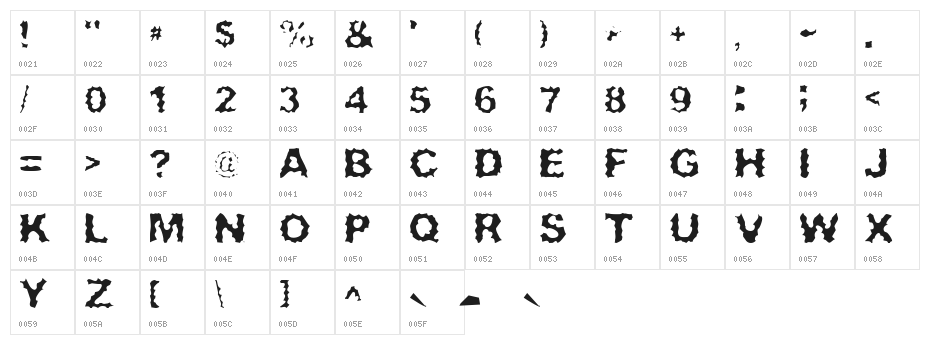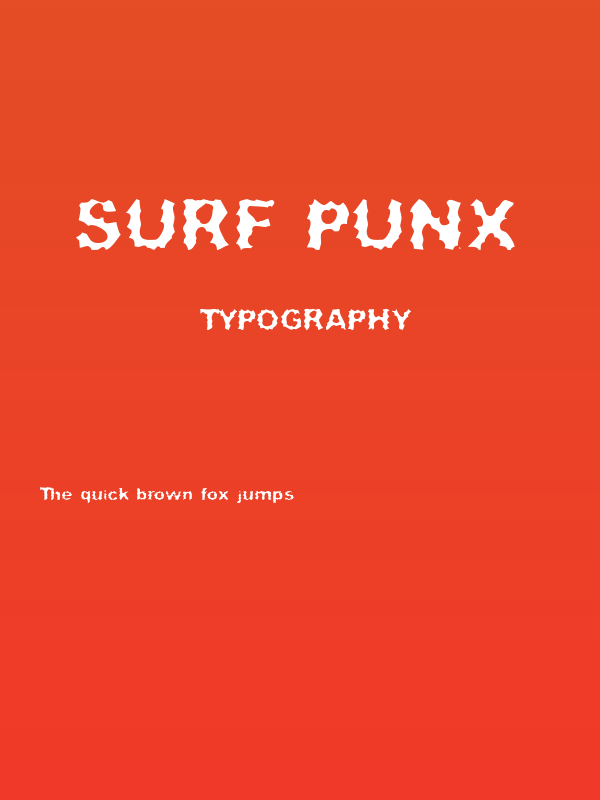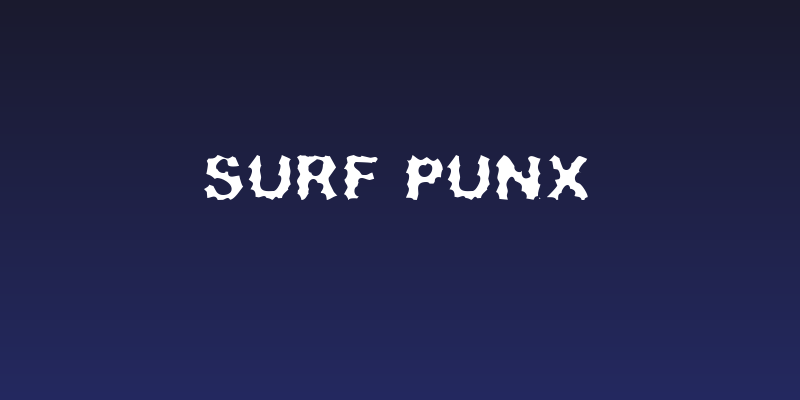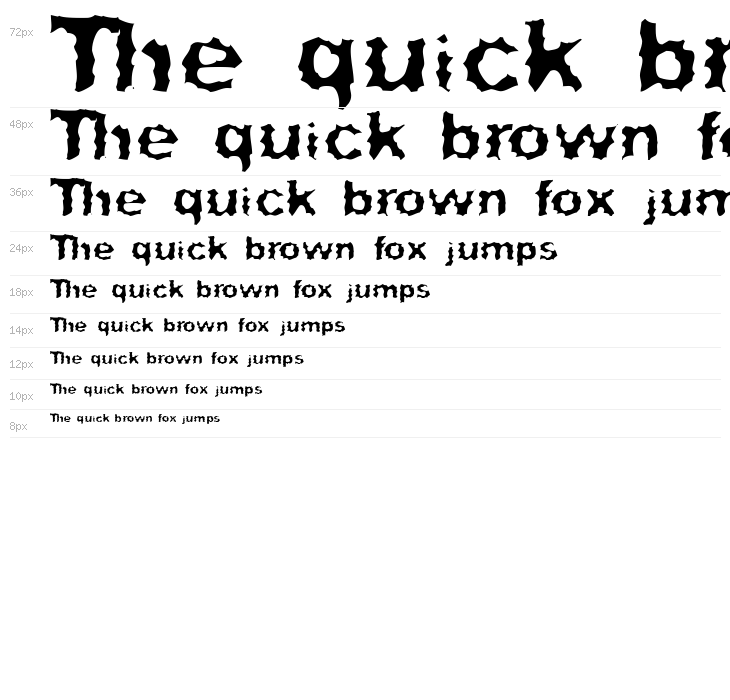
Surf Punx Font
| श्रेणियाँ | Quirky |
| समग्र शैली | Modern, Edgy |
| उपयोग का मामला | Headlines, Logos, Posters |
| सुझाए गए प्रोजेक्ट | Album covers, skateboarding brands, graffiti art, punk-themed posters, and edgy fashion labels. |